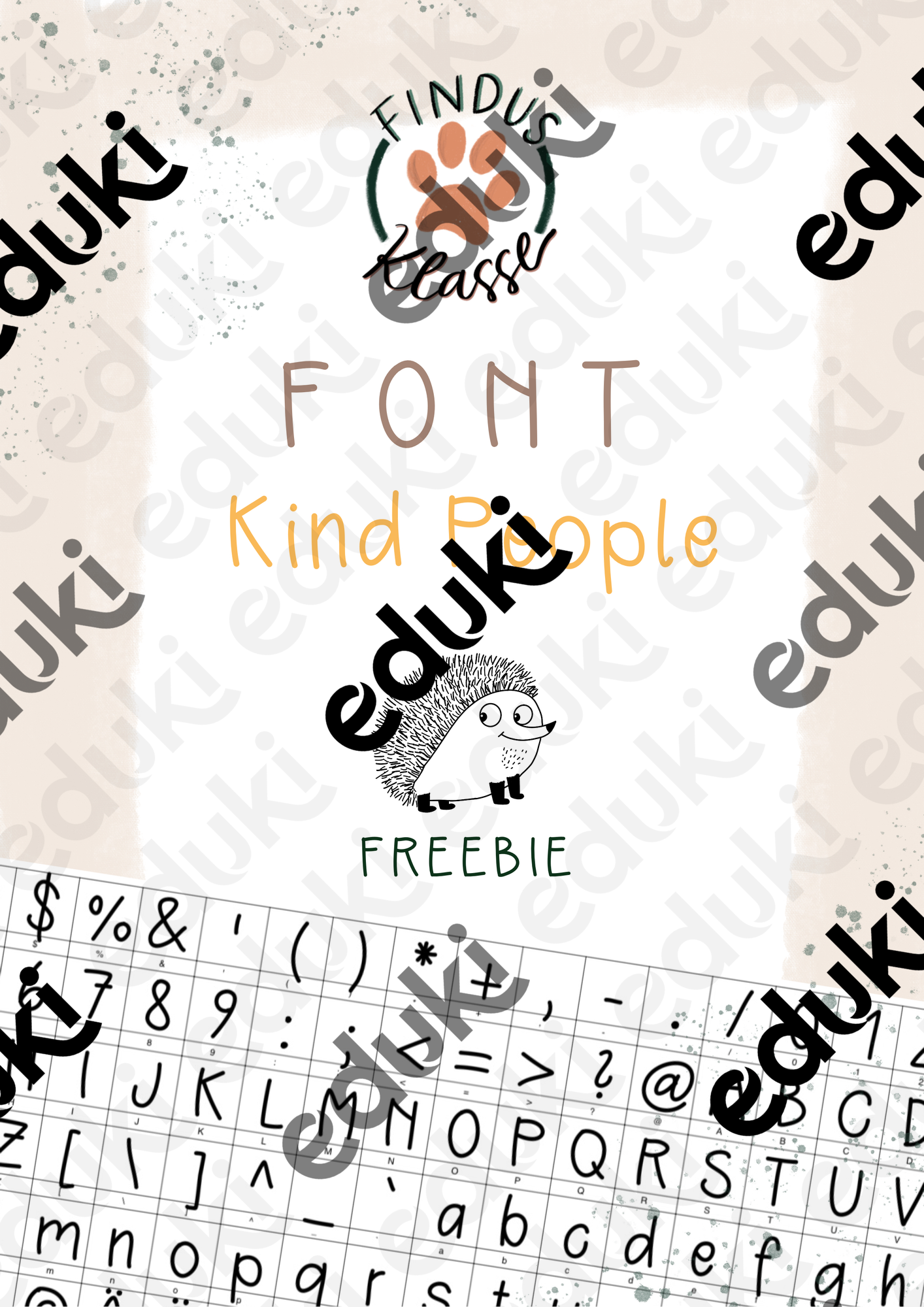
Mit KIND PEOPLE kannst du wunderbar Arbeitsblätter & co. verschönern. Eine nette Druckschrift für deine Materialien.
Font Findusklasse Kind People I FREEBIE
Ich liebe die Schriftarten von Findusklasse. So schön schlicht aber trotzdem niedlich! Für mich als Spanischlehrerin wäre es jedoch super, wenn auch das umgedrehte Fragezeichen und Ausrufezeichen dabei wären. Dankeschön und ganz liebe Grüße! :)